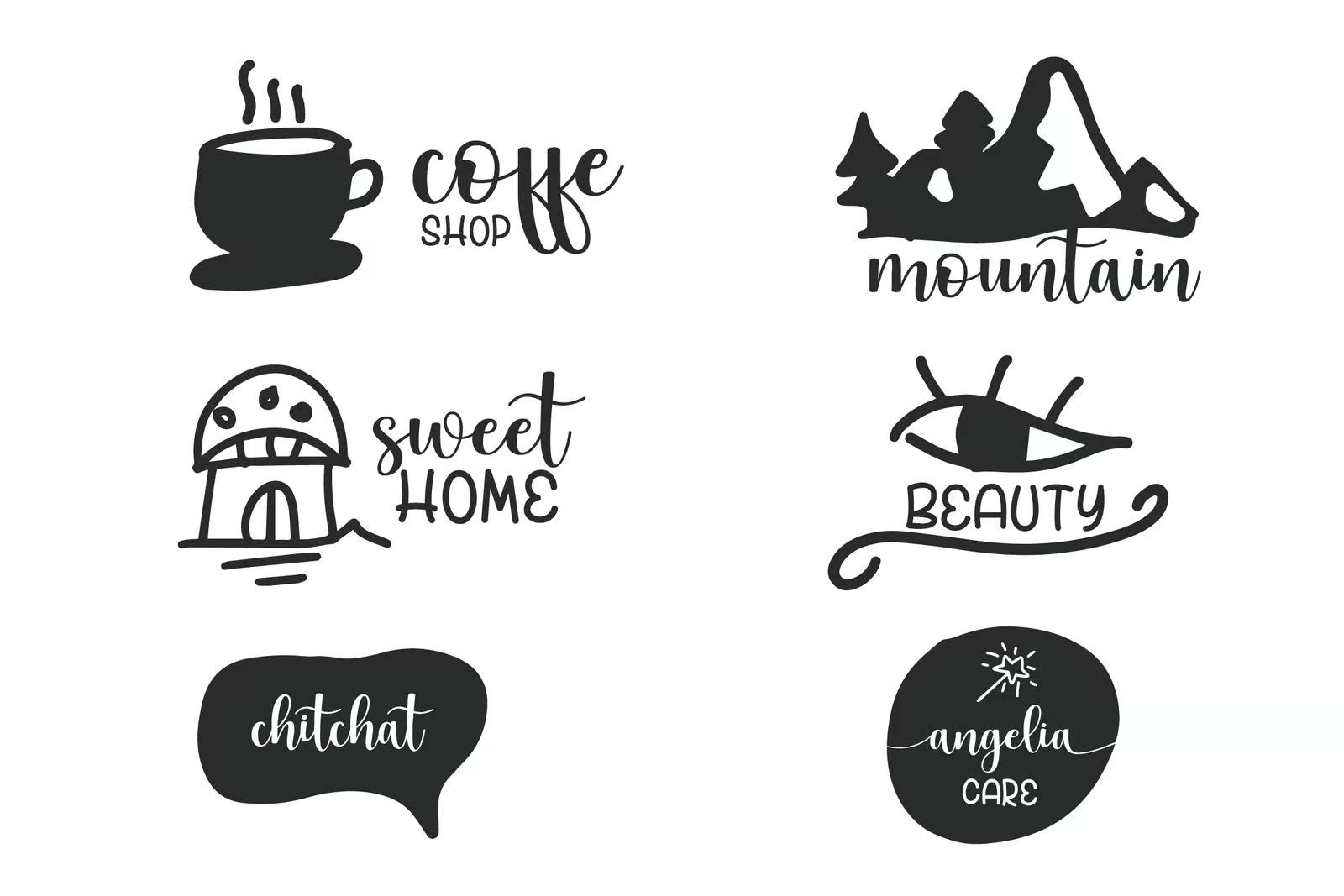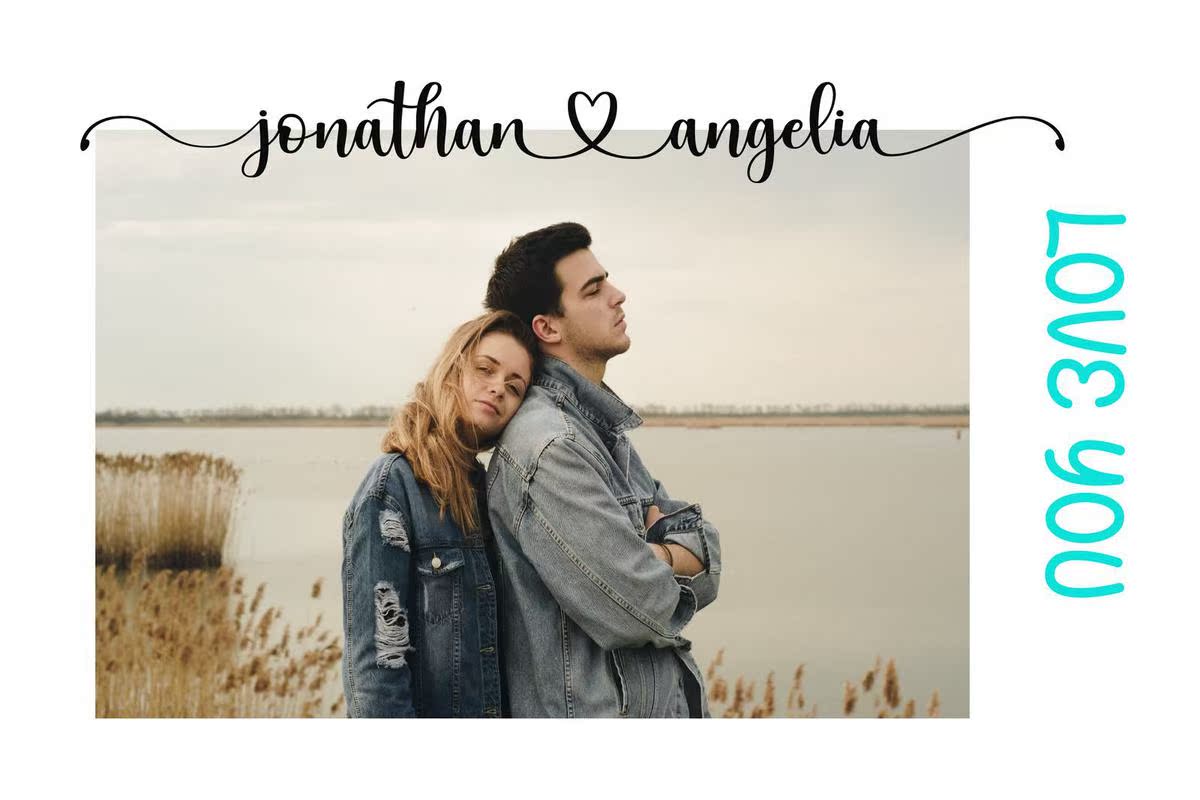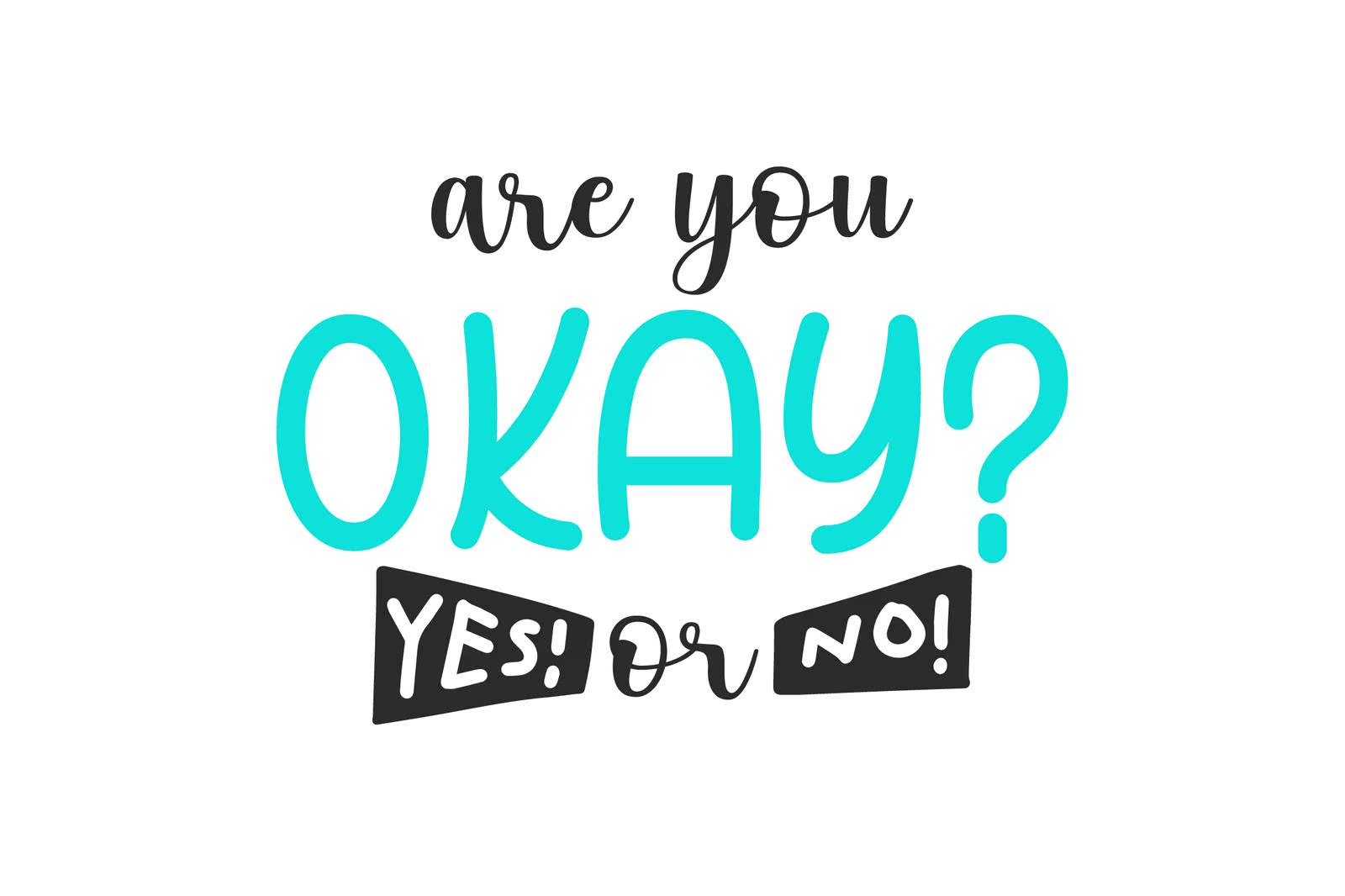
Holiday Sweet Lovely是一款引人注目的彩色字体,由沿基线移动的字符定义。这款字体功能多样,令人难以置信,它是一个设计池,将设计提升到了最高水平。令人惊讶的是,您的名片、报价、婚礼活动、问候卡、名片、,需要手动触摸的徽标和任何其他设计。此字体是经过编码的,表示您可以访问符号和开关!Holiday Sweet Lovely是一款引人注目的彩色字体,由沿基线移动的字符定义。这款字体功能多样,令人难以置信,它是一个设计池,将设计提升到了最高水平。令人惊讶的是,您的名片、报价、婚礼活动、问候卡、名片、,需要手动触摸的徽标和任何其他设计。此字体是经过编码的,表示您可以访问符号和开关!